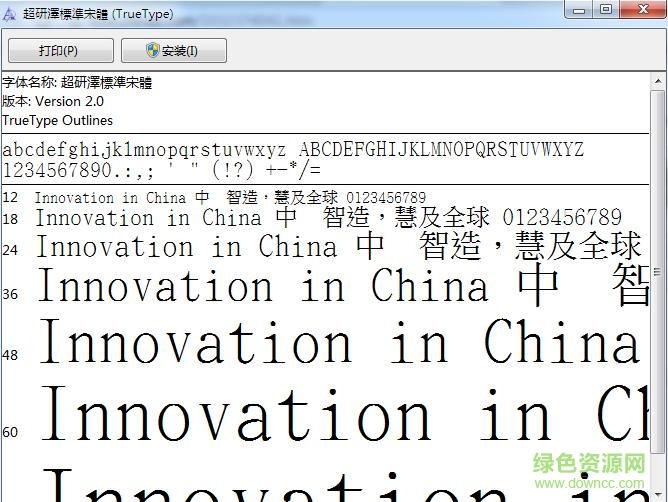
超研澤標(biāo)準(zhǔn)宋體是一款根據(jù)明代所創(chuàng)造的印刷字體打造的電腦字體,完美的將古代字體的特色融入其中,非常適合用作排版等,喜歡可以下載使用!
超研澤標(biāo)準(zhǔn)宋體是一款實(shí)用性很強(qiáng)電腦宋體字體,橫輕豎重,橫線尾和直線頭呈三角狀,字形端正、剛勁有力,常用于正文。